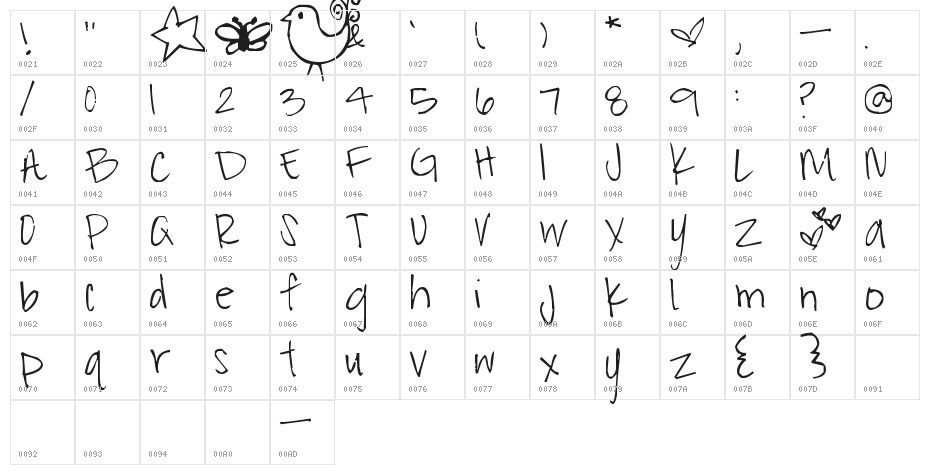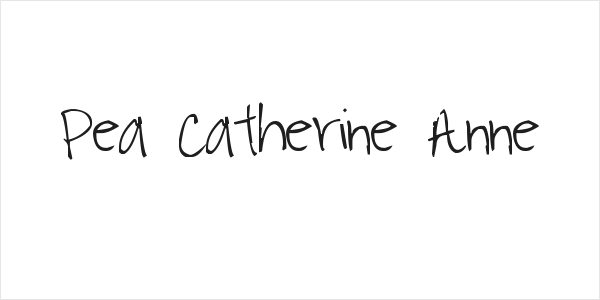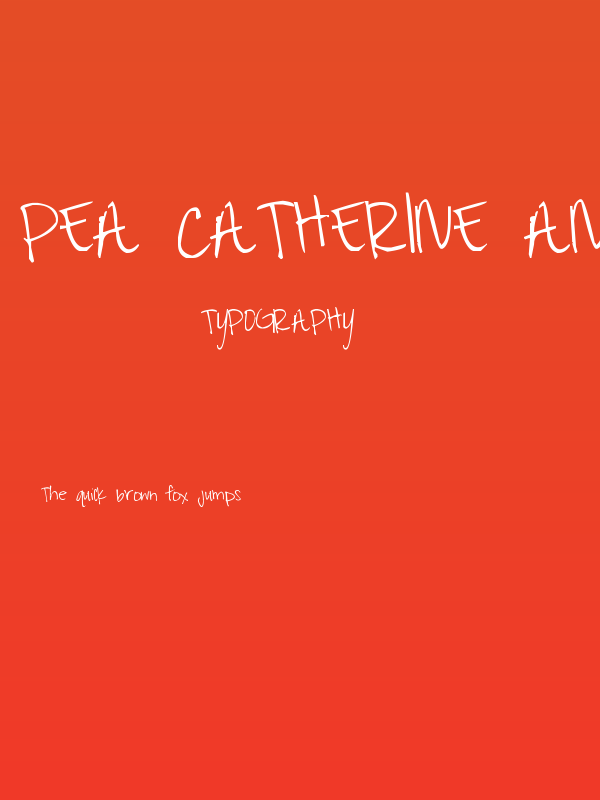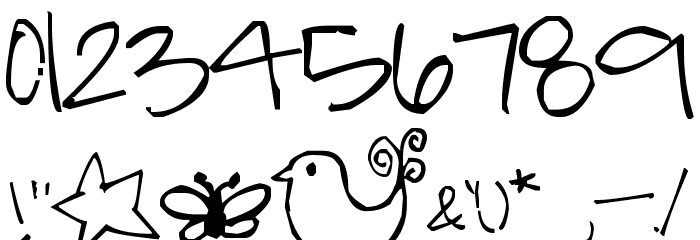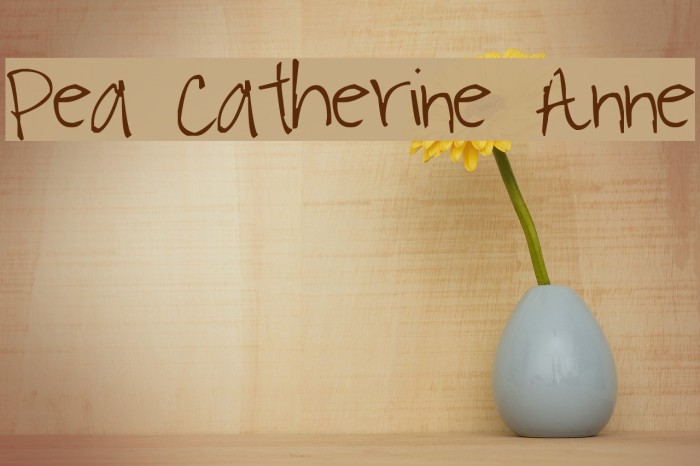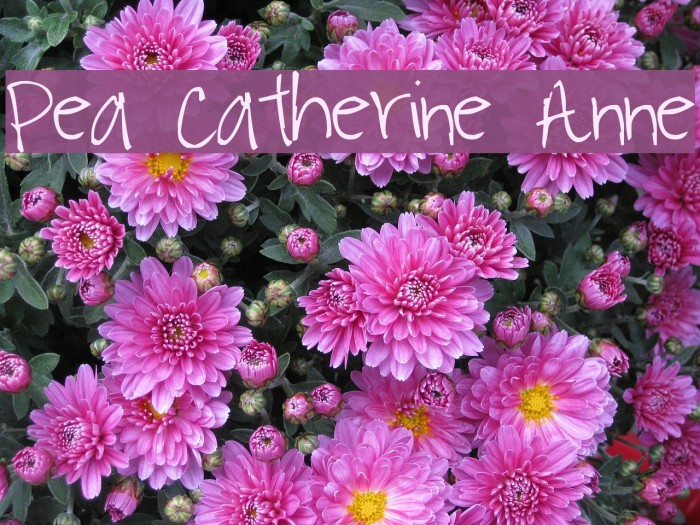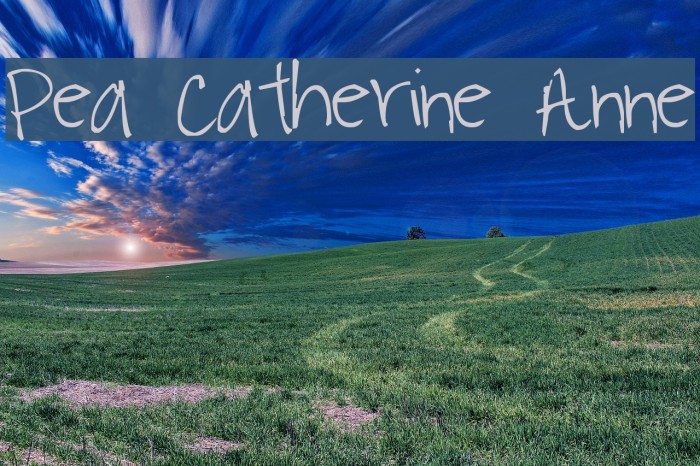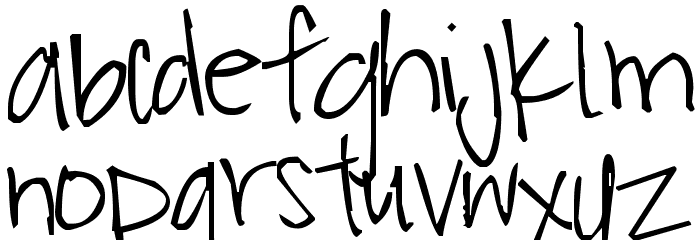
Pea Catherine Anne Font
| Stile generale | Casual |
| Caso d'uso | Headlines, Informal text, Creative projects |
| Progetti proposti | Ideal for greeting cards, children's books, personal blogs, and informal branding. |